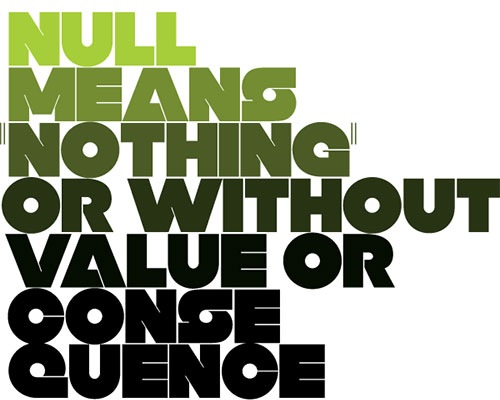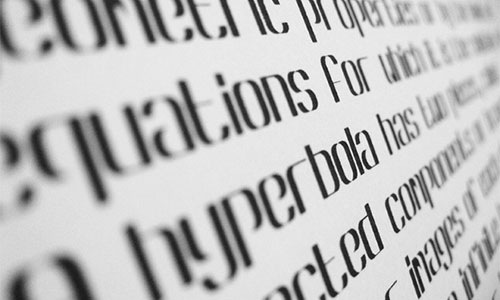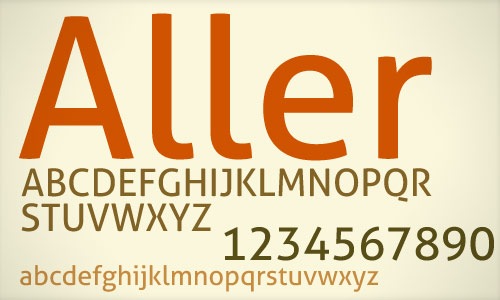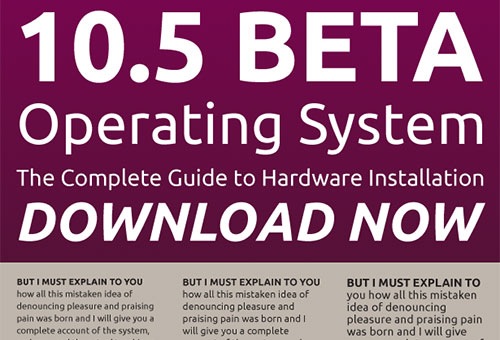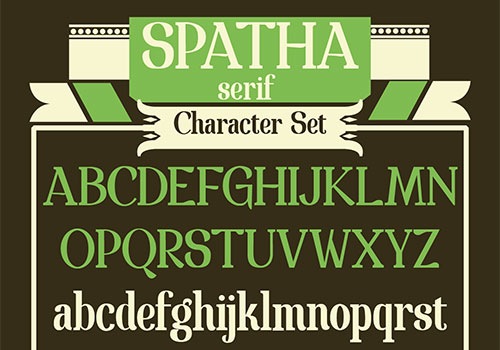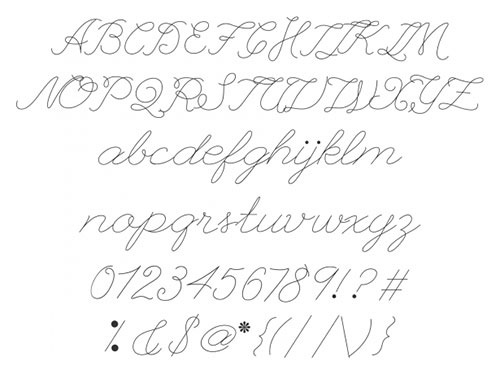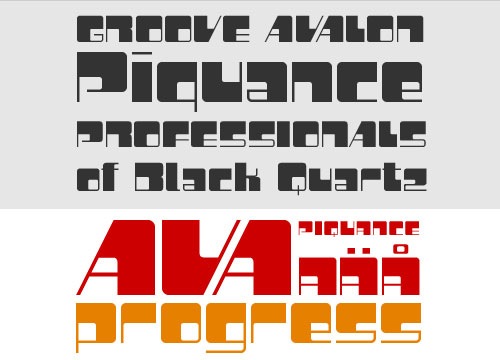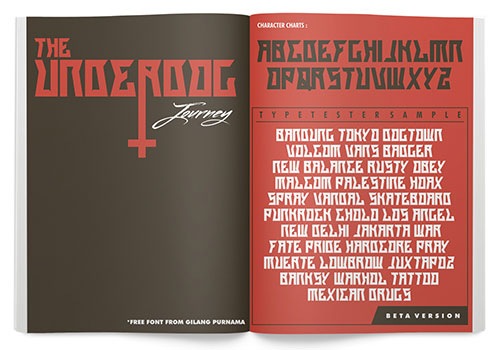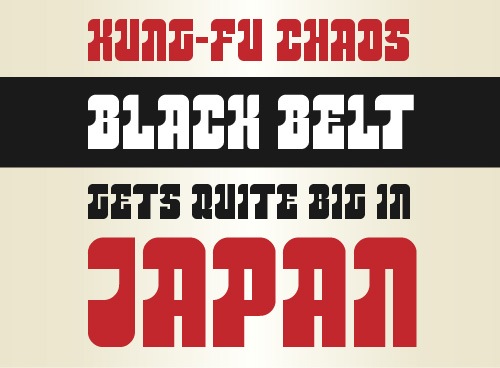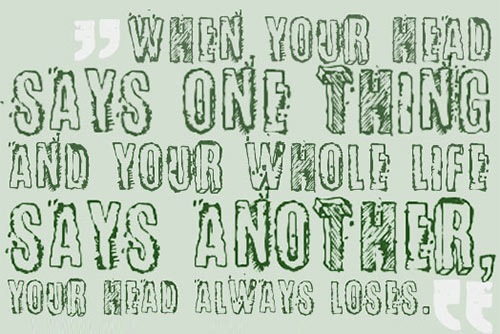
Более 40 бесплатных шрифтов для дизайнеров
шрифты Любой уважающий себя дизайнер, должен знать как правильно создать типографический проект и подобрать для этого нужный шрифт. Правильный выбор типографического шрифта, может преобразить обычный дизайн в привлекательное произведение искусства. Типографика очень эффективно используется в веб-дизайне, придавая ему определенный внешний вид, значительно отличающий его от обычного проекта.
Типографика очень мощный элемент в графическом дизайне. В нем читабельности шрифтов придается наименьшее значение, что дает возможность раскрыть потенциал художника, создавая типографические дизайны в художественной манере.
В подборке вы найдете множество популярных, художественных, а самое главное бесплатных типографических шрифтов, благодаря которым вы сможете сэкономить время, затраченное на их поиски в сети.
01. Шрифт Matilde
Шрифт Matilde
02. Шрифт под названием Practique
Шрифт под названием Practique
03. Шрифт Hero
Шрифт Hero
04. Шрифт Mobivus (Требуется регистрация)
Шрифт Mobivus
05. Шрифт под названием Null
Шрифт под названием Null
06. Шрифт Hyperbola
Шрифт Hyperbola
07. Шрифт Aller Standard
Шрифт Aller Standard
08. Яркий шрифт Color-Lines
Яркий шрифт Color-Lines
09. Шрифт Perforama
Шрифт Perforama
10. Аккуратный шрифт Clean (Требуется регистрация)
Аккуратный шрифт Clean
11. Необычный шрифт ROKE1984
Необычный шрифт ROKE1984
12. Шрифт Ubuntu
Шрифт Ubuntu
13. Угловатый шрифт SPOKEROOM
Угловатый шрифт SPOKEROOM
14. Креативный шрифт Now!Grotesk
Креативный шрифт Now!Grotesk
15. Красивый шрифт Spatha serif
Красивый шрифт Spatha serif
16. Тонкий шрифт ALT Lautus Thin (Требуется регистрация)
Тонкий шрифт ALT Lautus Thin
17. Прописной шрифт League Script Thin
Прописной шрифт League Script Thin
18. Простой жирный шрифт Low File
Простой жирный шрифт Low File
19. Объемный шрифт SayTwo
Объемный шрифт SayTwo
20. Стильный креативный шрифт Piquance (Требуется регистрация)
Стильный креативный шрифт Piquance